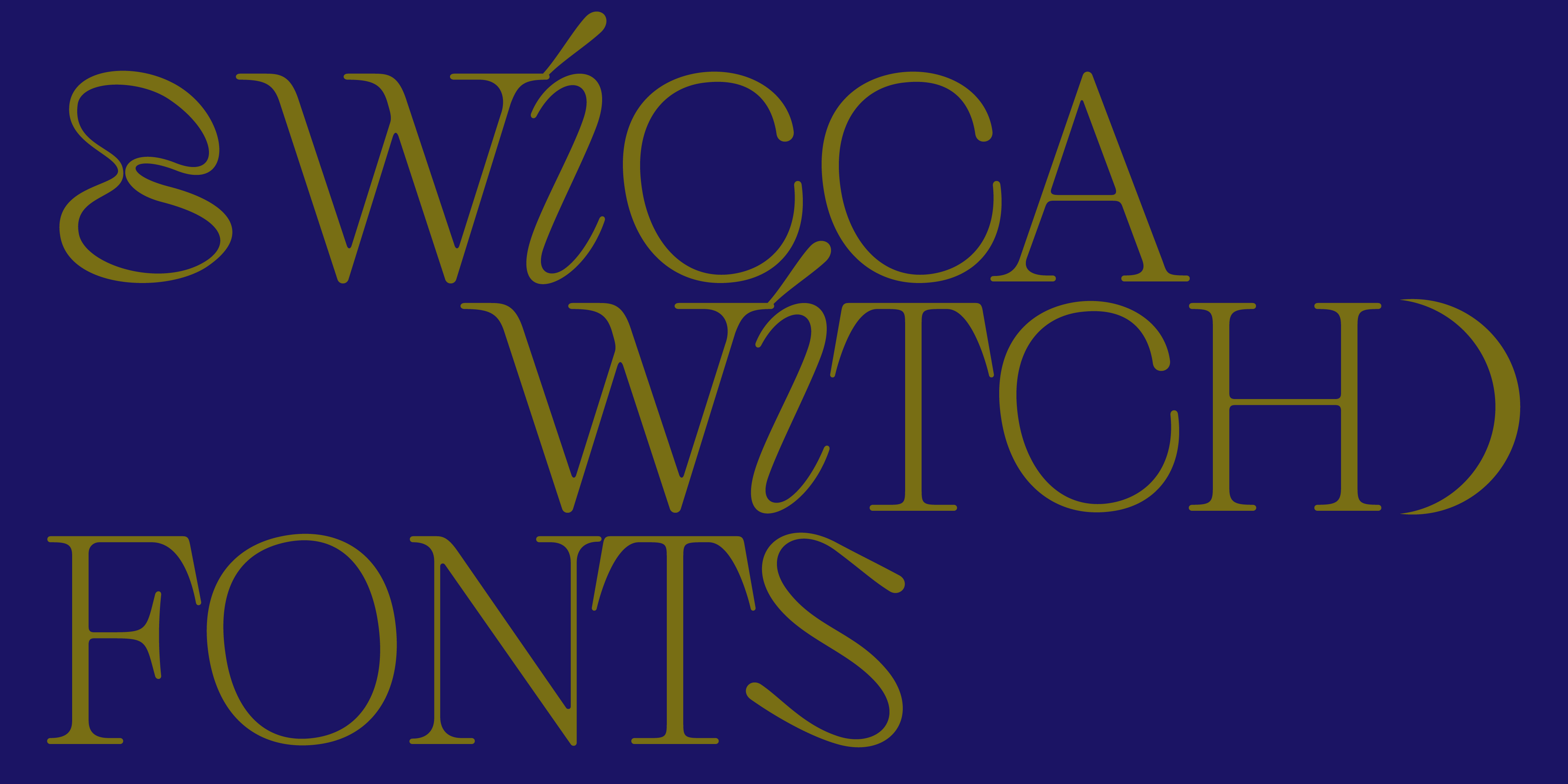
La magia de la brujería siempre está en nuestras mentes, así que echemos un vistazo a ocho nuevas y geniales fuentes hipster para carteles de Halloween, portadas de ficción de brujas marinas y letras de runas malvadas.
Fuentes serif de estilo bruja en contraste
Kijs es una fuente completamente nueva con un aspecto natural que funciona bien como fuente de texto, con un toque de fantasía. Esta tipografía tiene nueve grosores, desde finos hasta gruesos. Algunas letras, como las i y j, parecen una varita mágica: se destacan porque están inclinadas, lo que le da un toque sobrenatural a esta tipografía serif. Escribe Kijs Thin en mayúsculas para lograr un estilo más malvado.
La misma tipografía, pero con un grosor más grueso : Kijs Bold (también están disponibles ExtraBold y Black) añade un aspecto de bruja hipster a cualquier portada de ficción. Es fluida y le da a las letras una sensación genuinamente orgánica.
Bauhaus Soft es una tipografía serif redondeada que crea títulos elegantes cuando se usa en letras mayúsculas en un peso más delgado, por ejemplo ExtraLight .
Quil es una fuente serif moderna y contrastante con un toque moderno. La cola de la Q y los extremos afilados de esta tipografía tienen un aspecto contemporáneo y moderno.
Arriba se muestra la misma fuente en negro , el grosor de fuente más audaz disponible. Eche un vistazo a otra característica de diseño interesante: las letras B y R incluyen un swoosh, que agrega un poco de magia y modernidad a esta tipografía. Los grosores más audaces muestran aún más el alto contraste; las serifas cortas casi desaparecen, pero las terminales están cortadas, lo que la convierte en una fuente de brujas fuerte.
Fuentes para letras elegantes de brujas
Bauhaus Roma Regular es una fuente de contraste sin serifa que luce elegante y femenina en grosores de fuente más delgados. Los extremos son redondeados (por ejemplo, las letras a y r).
Una fuente más robusta que funciona bien para títulos de libros y fotografías de productos es Bauhaus Mod Black. Esta tipografía es un equilibrio entre una fuente de contraste moderna combinada con terminales de bola redondeados y puntos i grandes.
Dos fuentes de brujas para mostrar una personalidad divertida.
Por último, una tipografía divertida para los wiccanos es Bool Black, una opción excelente para proyectos mágicos para niños debido a sus puntas afiladas (letras M, W) y su apariencia geométrica y gruesa.
Si buscas personalidad, fíjate en esta tipografía manuscrita llamada Skay Light : sus letras mayúsculas nos recuerdan a palos y varitas.